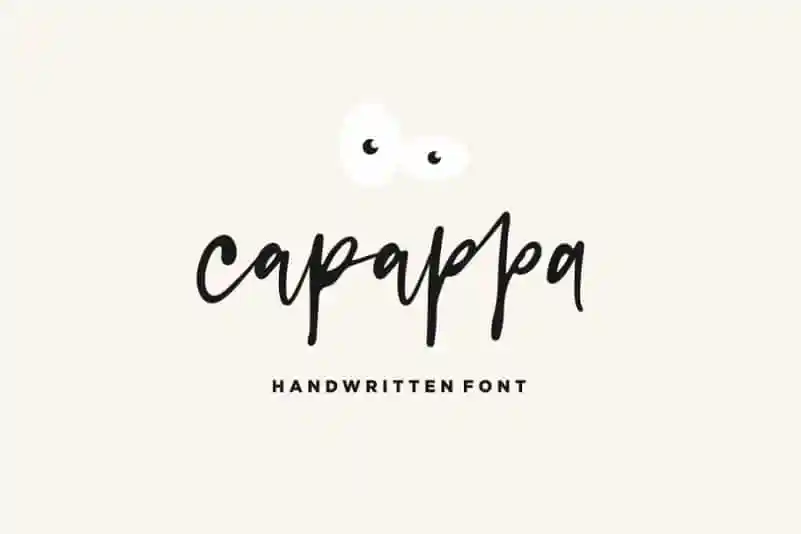
Através de sua elegância natural e seu próprio fluxo único, a fonte ‘Capappa Handwritten’ oferece uma experiência visual única e criativa para designers. Desenvolvida por M.0Type, essa font é ideal para um vasto conjunto de aplicações, incluindo logotipos, convites, materiais de embalagem, designs nupcionais, postagens na mídia social, anúncios, embalagens de produtos, rótulos, fotografia e até mesmo marcas especiais para eventos. Com uma completa variedade de letras maiusculas e minúsculas, alternâncias contextualizadas, símbolos multilíngues, números e pontuação, o ‘Capappa Handwritten’ está pronta para transformar seu design em algo realmente especial. Seja para um design gráfico ou até mesmo para adicionar uma marca única ao seu produto, esta fonte é a escolha perfeita.